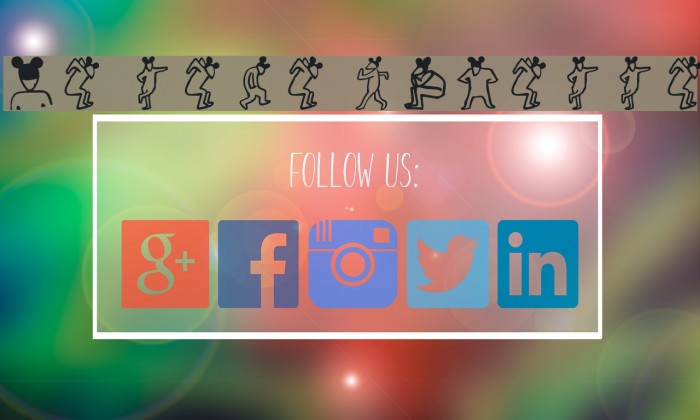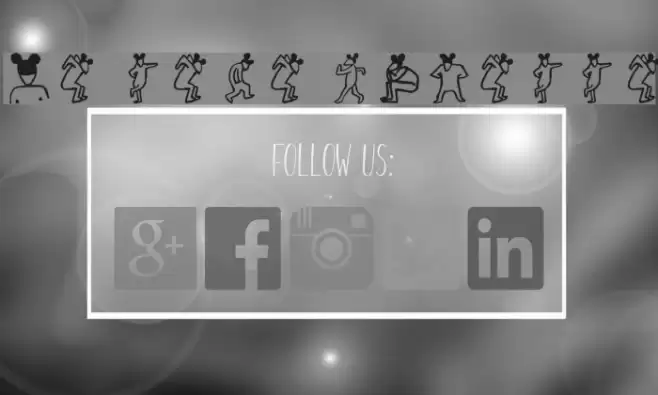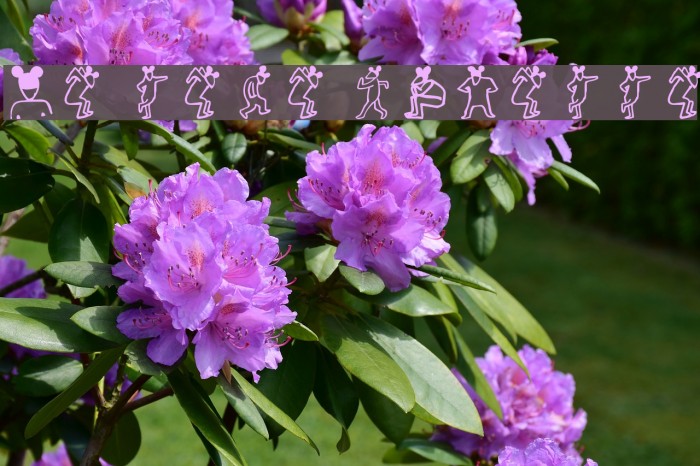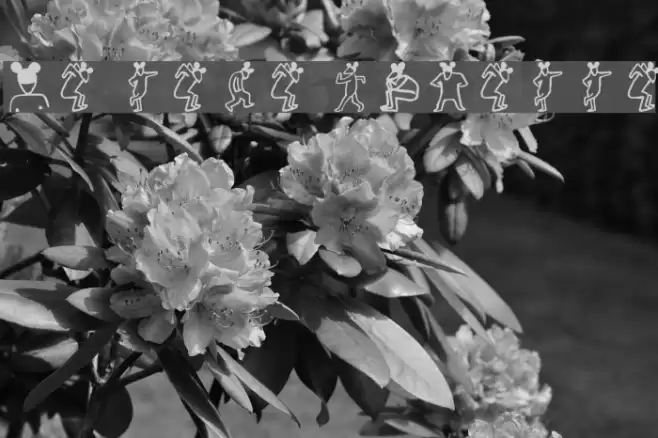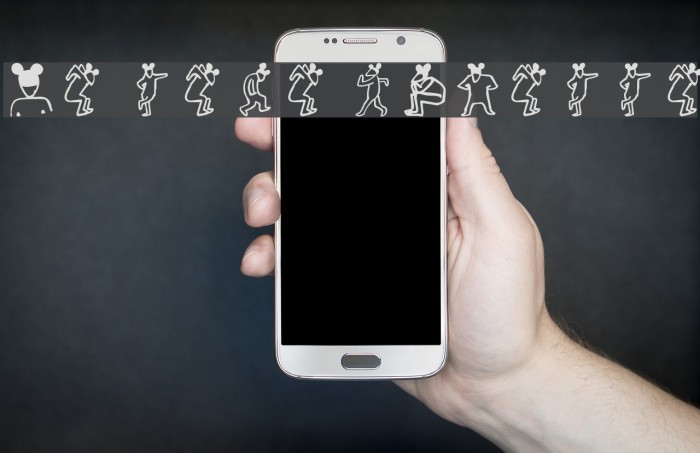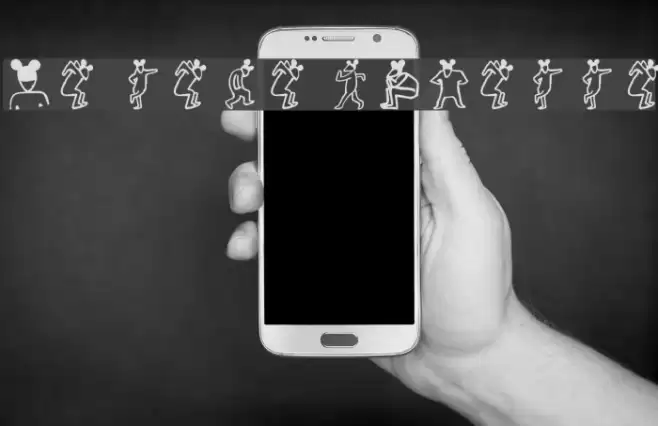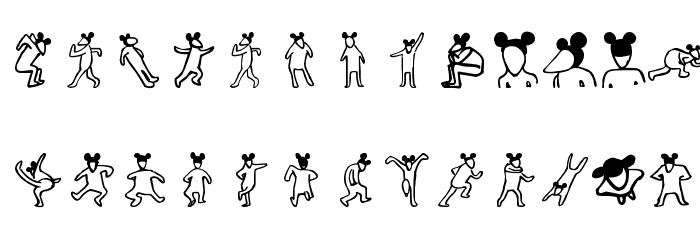
la rata bizarra Font
| Estilo geral | Whimsical, Playful, Artistic |
| Caso de uso | Logos, Headlines, Posters, Artistic projects |
| Projetos propostos | Children’s books, event posters, playful branding, party invitations, creative art projects. |